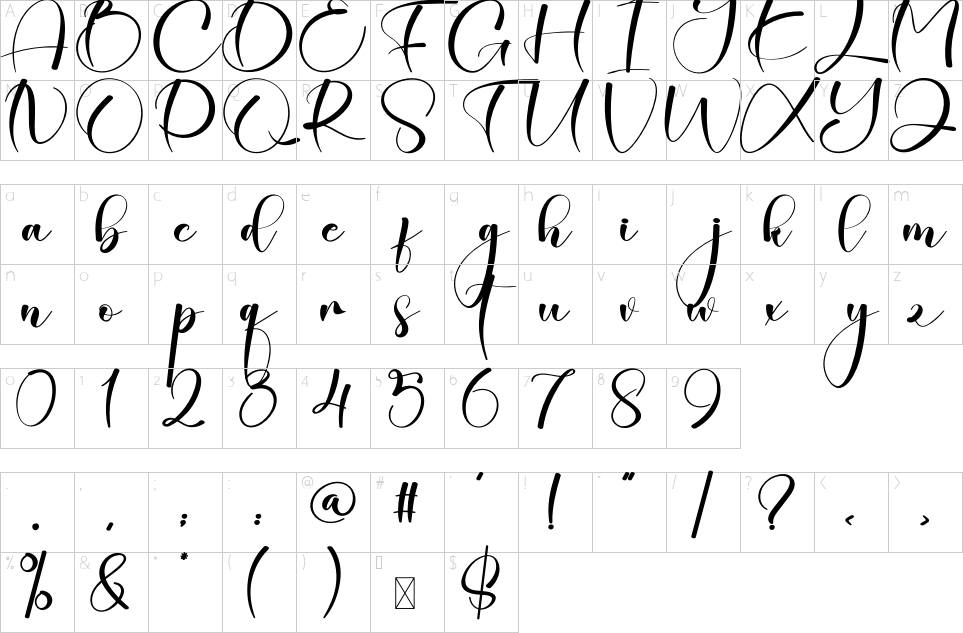
Donuts Christmas Font – Download Grátis
Aqui está uma versão em português do Brasil da descrição solicitada para a página de download da fonte ‘Donuts Christmas Font’: Descubra e descarregue gratuitamente a linda fonte Donuts Christmas, disponível tanto no Windows quanto no Mac. Esta elegante tipografia foi criada por scratchones e já foi baixada 356 vezes. Através desta fonte única, você pode adicionar um toque de festa natalícia à sua próxima mensagem ou design gráfico. Perfeita para personalizar cartas, criar listas compradas ou até mesmo decorar seu site com o espírito do Natal! Com a Donuts Christmas Font, faça sua arte e seus projetos brilharem ainda mais em tempo de festa.